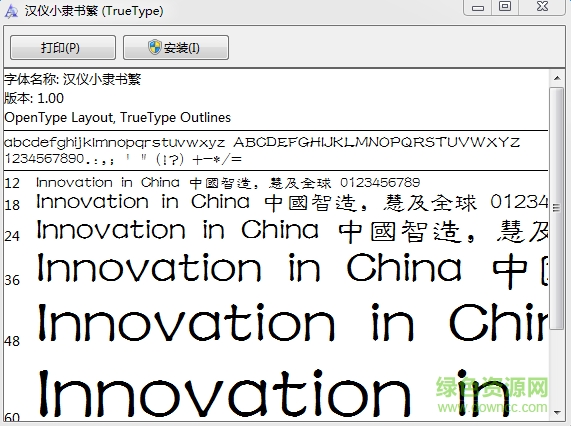
繁體隸書字體大全收錄了方正隸書繁體、漢儀小隸書繁體、禹衛(wèi)書法隸書繁體等一系列實(shí)用的隸書字體,字形工整,勻稱美觀,歡迎大家在綠色資源網(wǎng)下載!
1.它起源于秦朝,在東漢時(shí)期達(dá)到頂峰,書法界有“漢隸唐楷”之稱。也有說法稱隸書起源于戰(zhàn)國時(shí)期。
2.隸書也叫“隸字”、“古書”。是在篆書基礎(chǔ)上,為適應(yīng)書寫便捷的需要產(chǎn)生的字體。
3.隸書是漢字中常見的一種莊重的字體,書寫效果略微寬扁,橫畫長而直畫短,講究“蠶頭燕尾”、“一波三折”。